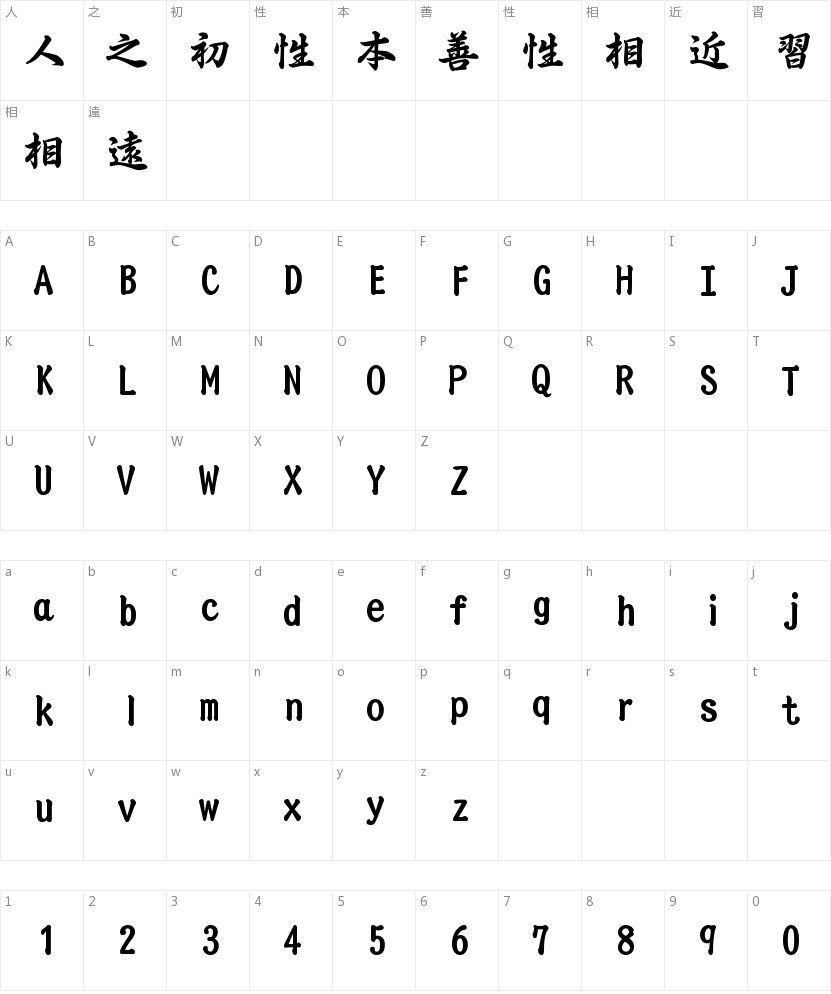
? 方圆行书书法是一种汉字书法,是汉字书写的一种技巧,它以“方”和“圆”两个概念为基础,由汉字的笔画组成,以“方”和“圆”两种笔画组合而成,具有极高的节奏感和美感。方圆行书书法的字体特点是:笔画清晰、结构紧凑、笔画细腻、笔画宽度均匀,书写整洁、按照规则组织,并具有节奏感和美感。文件名:FangYuanXingShuShuFa-1.ttf
方圆行书书法是一款非常不错的手写艺术字体,具有很好的视觉感,适合于文化类的宣传设计、商业类品牌的广告和产品包装设计以及个性化文字排版等较多场景。